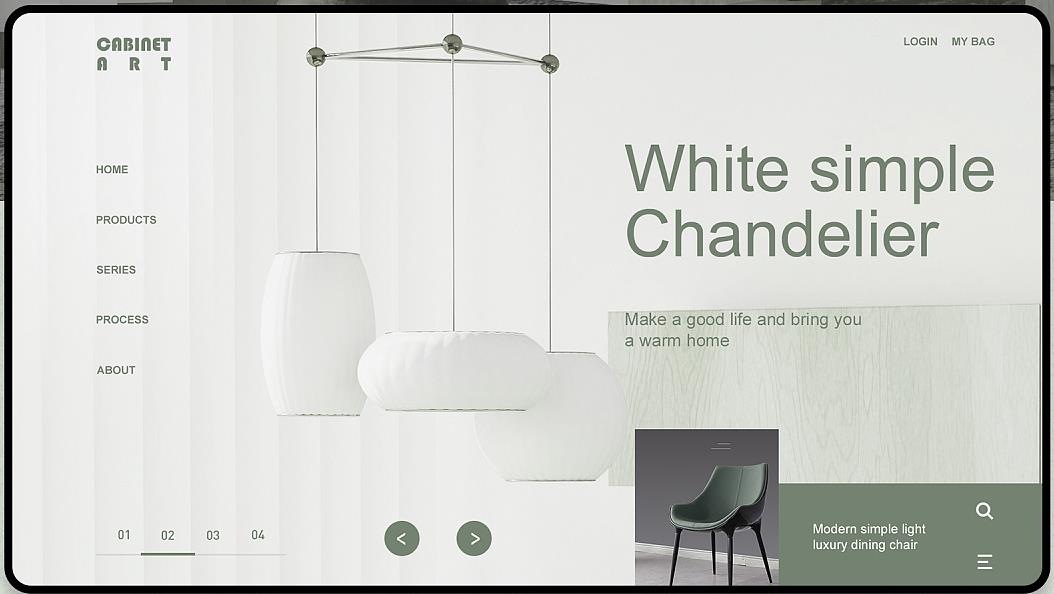
字体是网页设计中至关重要的元素,它们可以极大地影响用户对网站的体验。合适的字体选择可以提升可读性、创造视觉吸引力,并传达品牌信息。
字体类型
字体可以分为两大类:衬线体和非衬线体。
- 衬线体:这类字体具有小的笔触末端,称为衬线,它们通常给人以传统和正式的感觉。
- 非衬线体:这类字体没有衬线,它们看起来更现代和简洁。
字体大小
字体大小对于可读性至关重要。对于正文文本,建议使用 14-16 像素的字体大小。标题和副标题可以使用更大的字体大小。
字体颜色
字体颜色应与背景形成鲜明的对比,以确保可读性。对于正文文本,黑色或深灰色是不错的选择。对于标题和其他强调元素,可以使用更亮或更有对比度的颜色。
字体组合
在网页设计中使用多种字体可以创造视觉吸引力并传达不同的信息。但是,建议只使用两种或三种字体,以避免视觉上的杂乱。
字体配对
当组合不同的字体时,选择互补的字体很重要。衬线体和非衬线体的组合可以营造经典而现代的感觉。同时使用两种不同风格的衬线体可以创造视觉上的趣味。
字体与品牌
字体可以成为品牌标识的重要组成部分。选择反映品牌性格和风格的字体。例如,一家奢侈品公司可能会使用经典的衬线体,而一家科技公司可能会使用现代的非衬线体。
可读性
可读性是网页设计中最重要的方面之一。字体选择对于确保文本易于阅读至关重要。避免使用过于花哨或难以辨认的字体。
视觉吸引力
字体还可以创造视觉吸引力。使用醒目的字体和颜色组合可以吸引用户的注意力并创造一个难忘的体验。
传达信息
字体还可以用来传达信息。例如,衬线体可以传递传统和可信度,而非衬线体可以传递现代和创新。
结论
字体在网页设计中扮演着重要角色,可以极大地影响用户对网站的体验。通过仔细选择字体类型、大小、颜色、组合、配对和考虑可读性和品牌一致性,设计师可以创建既美观又有效的网页。